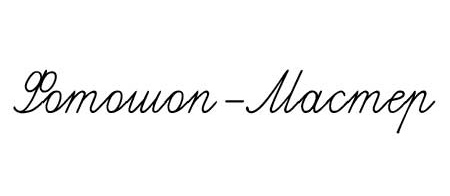
Спасибо, шрифт отличный, хотелось бы ещё букву а вот такую
Для школы самое то!
Здорово,очень хороший и нужный шрифт.
у меня такой же почерк))) прямо точ в точ))
Помню нас учили так писать.
cyegvevhbr, это потому, что эти буквы не бывают большими
у меня при использовании этого шрифта не отображаются буквы Ы, Ь и Ъ
Спасибо автору, очень хороший шрифт. Понятный и удобно использовать в большом тексте.